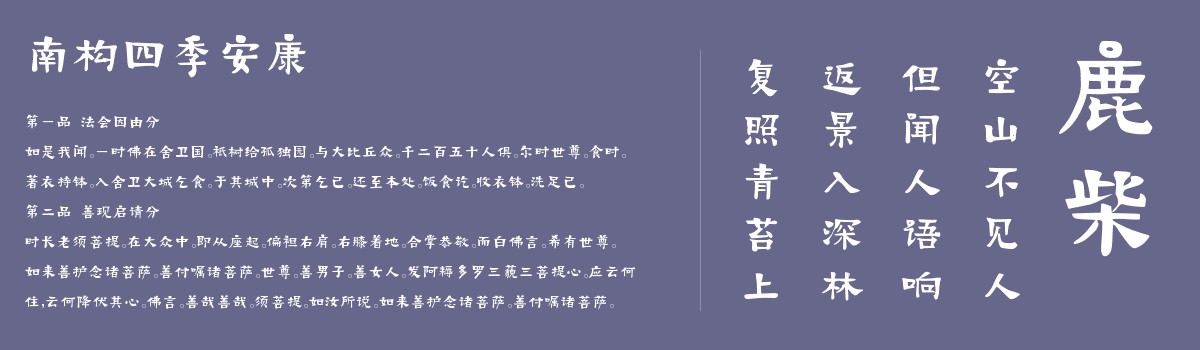
南构四季安康
南构四季安康是一款由字体家AI神笔造字生成的艺术字体,笔画圆融温润,起收处无尖锐棱角,如鹅卵石般平滑过渡。横画竖画粗细匀净,似精心削制的竹筷,挺直却不僵硬。整体气质端庄谦和,无张扬笔锋,却有内敛的温润感,像冬日里晒暖的木桌,坚实中透着亲和,耐看且舒适。适合用于一些广告标题、平面文案、海报标题、网页广告用字的编辑。